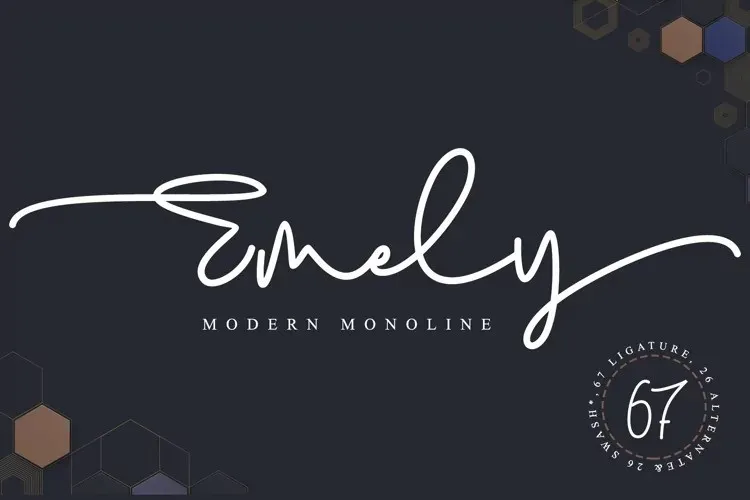
Esta é uma fonte script monolínea que Thomas Aradea criou com delicadeza e romantismo. Ideal para designers buscando um estilo elegante e cálido, essa fonte pode ser usada em designs diversos como headlines, títulos, logomarcas, convites, livros e muitos outros trabalhos de criação. Com acesso fácil a todos os gílitos encantadores e ligaturas alternativas, essa font é perfeita para aqueles que valorizam uma gravação legível e sofisticada. Como um arquivo PUA codificado, você pode facilmente acessar todas as características únicas desta fonte de script elegante. Seja para projetos simples ou complexos, a Emely Font oferece a perfeita combinação entre beleza e funcionalidade.